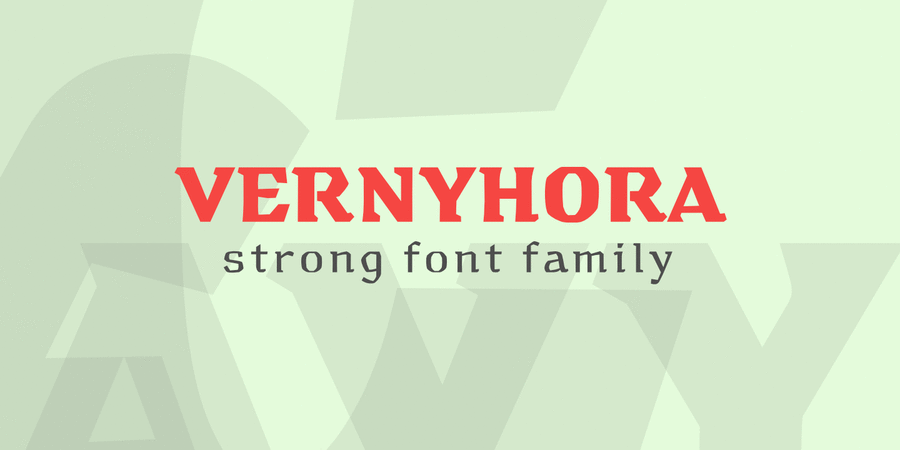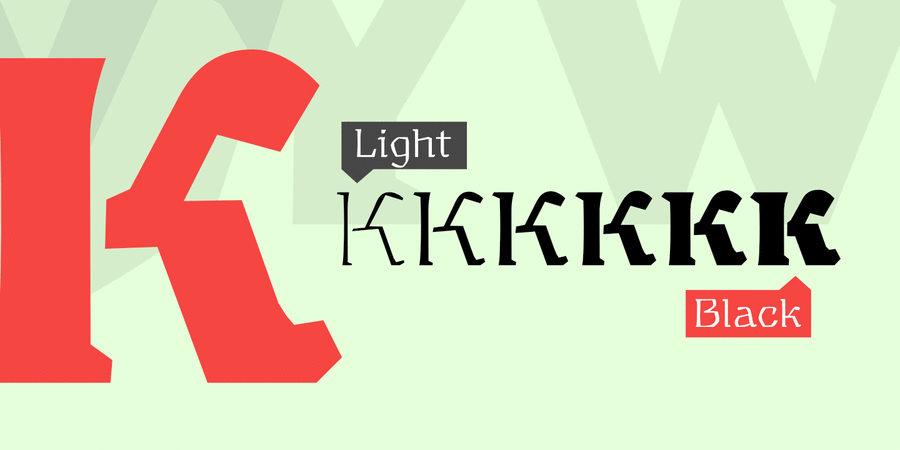
Опис гарнітури VernyhoraВінтажне акцидентне шрифтовое сімейство Вернигора. Шрифт призначений для місць, де літери повинні передавати сильний характер, надійність та історичну значущість. Гарнітура має 6 насиченостей та містить розширену кирилицю і латиницю. Також є альтернативний набір символів для староукраїнської абетки. Шрифт буде добре виглядати на вивісках державних установ. Спочатку Вернигора призначався для туристичних міст, з історичними кварталами, щоб позначати в'їзд у місто. Форма шрифту натхненна роботами українських графіків початку 20-го століття, таких як Георгій Нарбут та Федір Кричевський. Гарнітура містить 1 безкоштовне накреслення Vernyhora Demo EstraBold. Ви можете вільно використовувати його, але не розбирати і не видавати шрифт від свого імені. Ліцензія на Vernyhora Demo EstraBold: https://creativecommons.org/licenses/by-nd/4.0/deed.uk Шрифт Вернигора розробив Богдан Гдаль у 2017 році.
Особливості сімейства шрифтів VernyhoraХіт десятиліття:
Асоціації з сімейством шрифтів VernyhoraОсобистість і характер гарнітури:
твердий, вільний, тонкий, жорсткий, чіткий, історичний, самобутній, характерний, оригінальний, різкий, гострий, колоритний, артистичний, художній, динамічний, ремісничий, виразний, крафтовий, рубаний, холодний, крижаний, скляний, крихкий, прозорий, колючий, ламаний, племінний, артізанальний, худий, козацький, вольний, гордий, войовничий, хоробрий, бравий, мужній, сильний, темпераментний, мотивуючий, активний, амбітний, суворий, грубий, залізний, робочий, плоскінний, сірмяжний, сільський, релігійний, екологічний, добротний, стійкий, сміливий, етнічний, натуральний, традиційний, ностальгічний, переконливий, впевнений, рукотворний, консервативний, природний, бунтівний, героїчний, кам'яний, важкий, яскравий, помітний, потужний, масивний, солідний, наполегливий, чорний, тісний, сталевий
етнографія, скульптура, горілка, козак, гетьман, отаман, закуска, спеції, пиво, таверна, ремесло, коваль, тютюн, кіно, тату, татуювання, історія, музей, театр, алкоголь, реконструкція, фольклор, літопис, геральдика, ярмарок, хенд мейд, природа, здоров'я, сувенір, пам'ятник, меморіал, вишиванка, замок, легенда, зброя, захист, бій, мед, Трофей, нагорода, банкнота, монета, перець, робочий, пельмені, квас, хліб, баня, м'ясо, прапор, камінь, граніт, конструктор, гра, цегла, металургія, техніка, страйкбол, взуття, тара, танк, армія, блокбастер, бойовик, екшен Гарнітура асоціюється з віком: